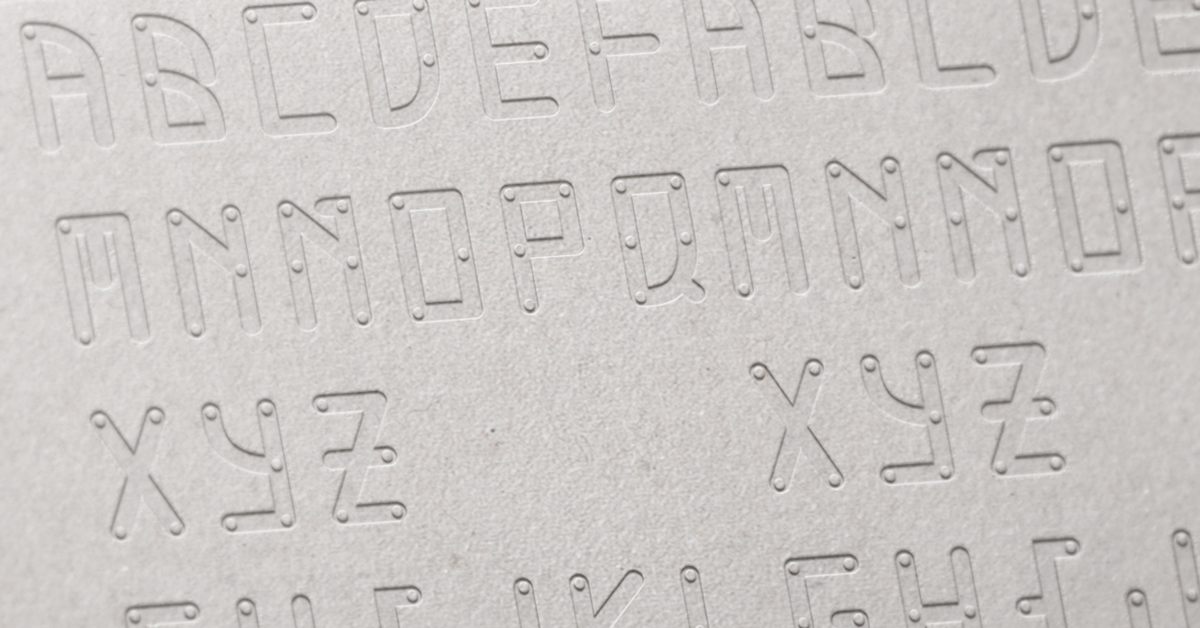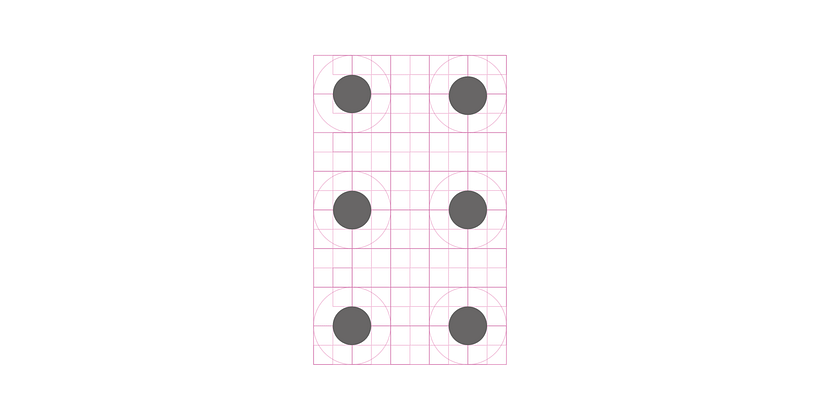
Blind words, la tipografía inclusiva para videntes e invidentes
Núria López ha creado un sistema tipográfico que permite leer a personas con cualquier tipo de capacidad visual.
"¿Es el diseño gráfico actual restrictivo con las personas invidentes?" fue la pregunta que Núria López (@srtaserifa) se hizo en el momento de concretar la idea detrás del diseño de Blind words. A la hora de responder esta pregunta la controversia está servida, sin embargo, Núria López lo tiene claro: el diseño debe de ofrecer una solución sostenible, ecológica o que respete la inclusión social; y es principalmente en este último punto en el que se apoya la tipografía que ha desarrollada y adaptada pensando en que pueda ser leída tanto por videntes como por invidentes.
Un proyecto de estas características precisa profundizar en aspectos que van mucho más allá del aspecto visual de la tipografía. Así, el diseño de Blind words se desarrolló en dos planos diferenciados: uno más experimental y otro funcional. La primera fase consistió en investigar métodos de impresión que permitiesen incluir las dos partes de la tipografía, una visual y otra que se pudiese leer con las manos. Combinando el sistema inventado por Valentin Haüy, que permitía a los ciegos leer a partir del relieve de las letras impresas, y el sistema braille, Núria López ideó el método de impresión ideal para su tipografía.
La vertiente más funcional del proyecto se refiere al diseño de la tipografía en sí. Tomando como punto de partida los seis puntos que conforman el alfabeto braille, Núria diseñó una fuente que representa todos los glifos del alfabeto latino en una cuadrícula que permite superponer uno sobre otro y responder a las necesidades de lectura tanto de invidentes como de invidentes.
El proyecto Blind words, de Núria López le ha granjead numerosos premios y reconocimientos, el último de ellos el Gaudeamus Proyecta, otorgado por el Col·legi Oficial de Disseny Gràfic de Catalunya.
@lagisteria Ciertamente se parecen, pero Blind Words es un proyecto tipográfico desarrollado antes que Braille Neue http://www.dissenygrafic.org/blind-words-versus-braille-neue/, el diseñador Kosuke Takahashi lo afirma al citar la tipografía de Núria López entres sus referentes http://brailleneue.com/#reference